フォントを作る人に聞いてみた その8:デザインするのが難しいグリフ2
タイププロジェクトのデザイナー達に「デザインするのが難しいと感じるグリフ」は何かを聞いてみました。
前回は画数について言及した回答を紹介しましたが、今回はその他の回答と欧文グリフについての回答も紹介していきます。
和文関連のグリフでは「ふ」を挙げた人が2名いました。どこをつなげてどこを離すかなど骨格のバリエーションも多いですしバランスを取るのが難しいグリフなのかもしれません。
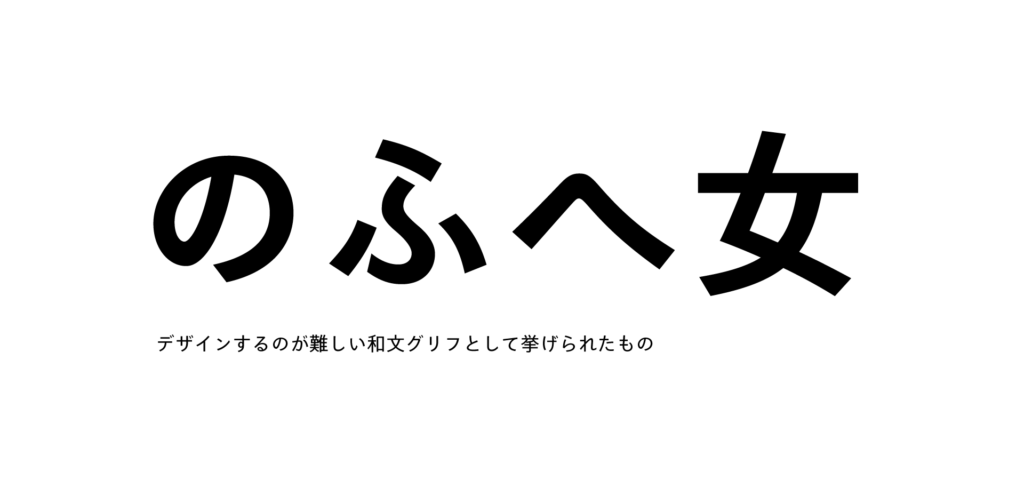
- 書体によって変わることが多いですが、意外に手こずるのが「へ」と「ふ」。
- 「の」「ふ」「女」:
「の」誤魔化しが効かない感じ
「ふ」バランスの取り方
「女」1、2画目の左払いの角度のバランス
欧文グリフについては「s」「y」が挙げられていました。
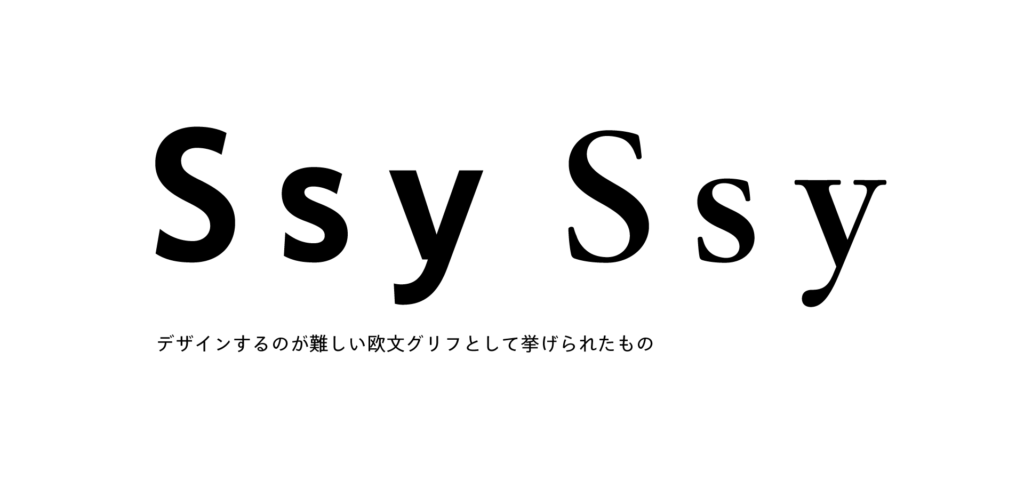
- S:
外と内の曲線のバランスと太さ
- S, s, y:
太さやカウンターの広さのバランスを取るのが難しい。 特に太いウェイトでは納得がいく形に仕上がるまで時間がかかる。
- y:
バランスが難しい
その他には音楽記号について言及していた回答もあります。 音楽記号は比較的使用する機会が少ないですが、フォントによってどうデザインが違うのか見比べてみると面白いかもしれません。
- ♪♯♭:
吹奏楽部だったのでイメージが出来すぎているのか、そのフォントらしさをどう入れていくか悩みました。
今回の質問は回答内容の個人差が大きかったですが多くの回答に「バランス」というワードが登場しました。
どういった形にデザインの難しさを感じるかは人それぞれでも、デザインをする上で「バランスを取ること」に着目するのはどのデザイナーにも共通している視点だということが伺えます。